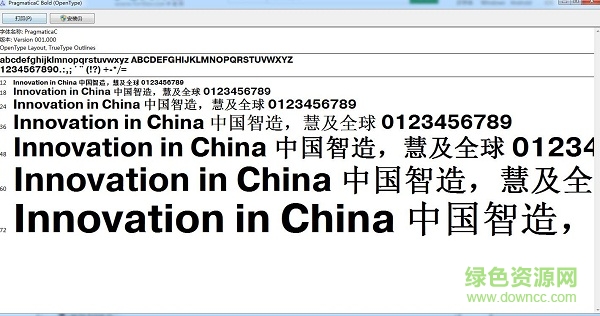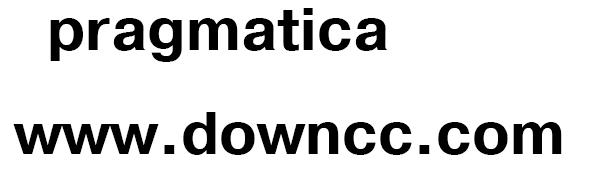
pragmaticac-bold
pragmaticac-bold字體是一款字面較大的無襯線字體,線條粗細均勻,橫豎基本一致,曲線非常的流暢干凈,大方、現(xiàn)代,富于現(xiàn)代氣息,有需要者歡迎在綠色資源網(wǎng)下載!
襯線與無襯線字體區(qū)別
serif強調(diào)一個word,而非單一的字母,反之sans serif則較強調(diào)個別字母;
在很小字的場合,通常sans serif會較serif字體較為清晰。
pragmaticac字體
中英文字體特點
明(宋)體就是serif的,他通常是和TimesRoman字族來搭配的,而黑體、圓體就相當于是sans serif的字體。